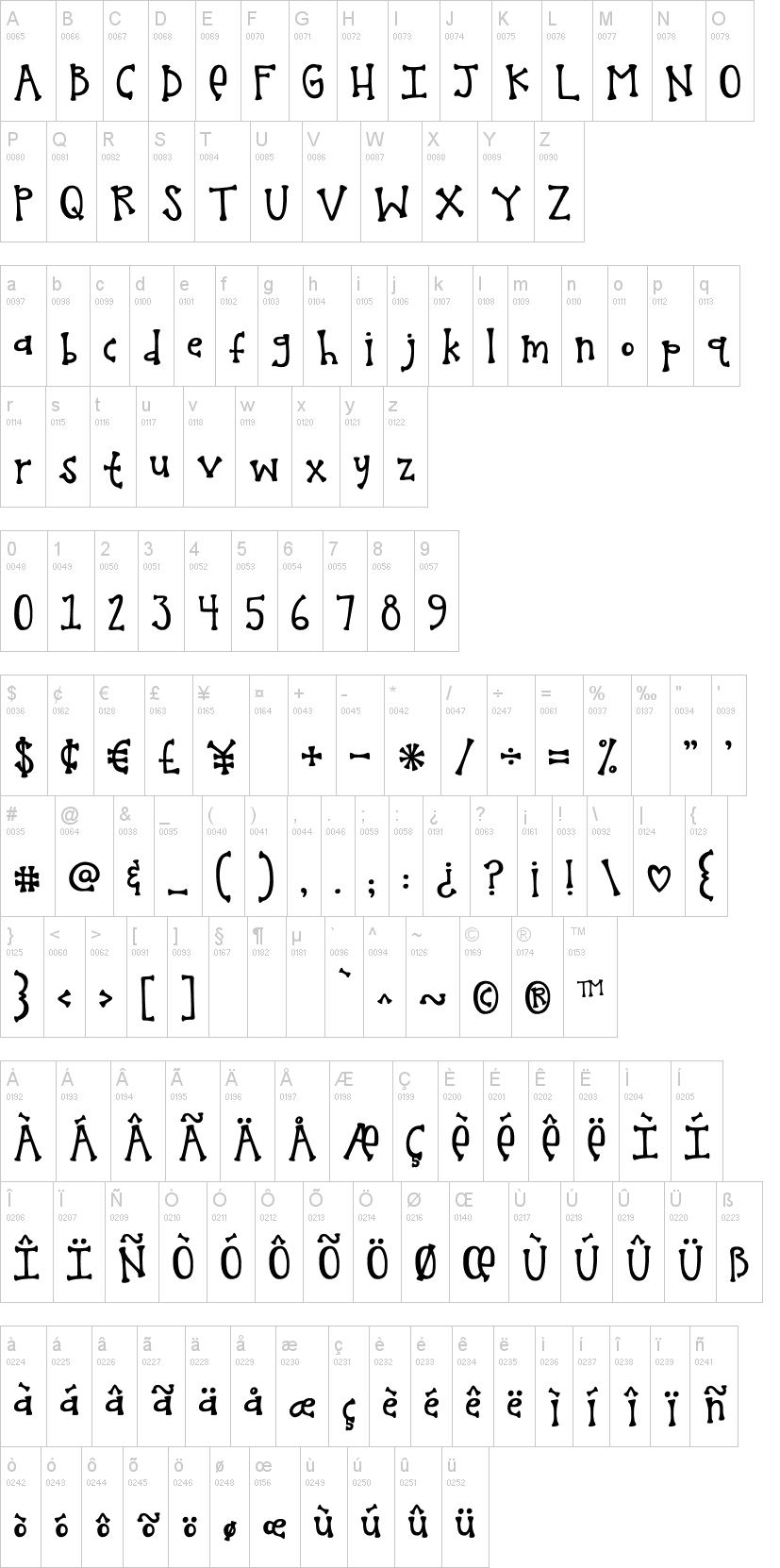
KG Melonheadz是一款由Kerry Goulder设计的字体,它具有轻松、可爱、可爱的外观,是一款温暖、友好的字体,适合用于各种涉及儿童的文档或设计。KG Melonheadz有大量的字体变体,可以满足不同的设计需求。它的外观让用户感觉自在、放松,是一款很受欢迎的字体。内容介绍
KG Melonheadz是一款非常不错的手写艺术字体,具有很好的视觉感,适合于文化类的宣传设计、商业类品牌的广告和产品包装设计以及个性化文字排版等较多场景。